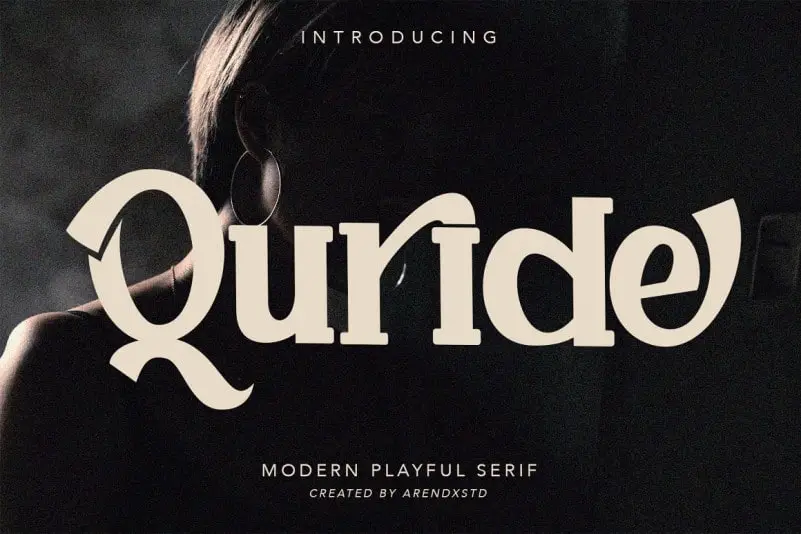
Quride Slab Serif Font – Download Grátis
A Quride Slab Serif é uma fonte tipo serifa estenográfica inspirada nos clássicos com um estilo retro e combinado com alternativas únicas e ligaturas. Esta fonte vem equipada com opção de estilo alternativo, conjuntos de estilo e ligaturas em OpenType, fazendo-a ideal para logotipos, posters, selos, capas de livros, t-shirts e embalagens, ou qualquer outra necessidade gráfica que você possa imaginar. Inspirada por fontes clássicas da década passada, a Quride é uma escolha perfeita se estiver procurando uma combinação única de clássico e contemporâneo para seus projetos visuais. Composta com um design robusto e forte, esta fonte será o elo perdido que seu próximo projeto visual precisava.